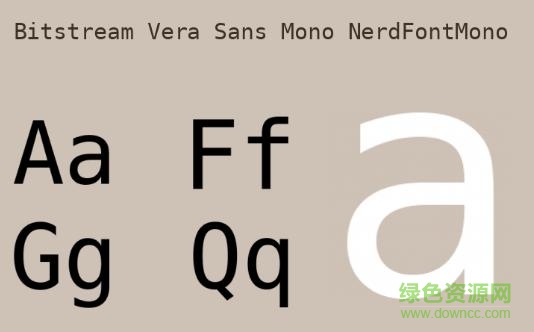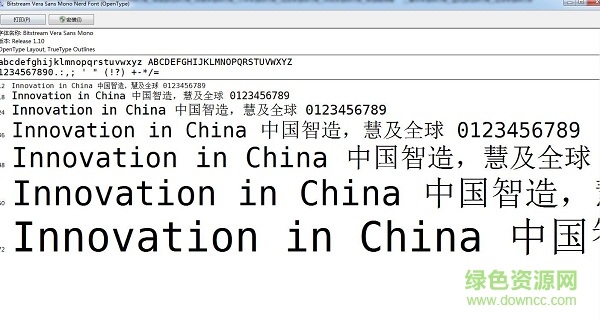
bitstream vera sans字體是一款線條清楚明朗的英文等寬字體,結(jié)構(gòu)端正,粗細(xì)一致,視覺效果不錯(cuò),適合用在電子排版以及網(wǎng)頁(yè)設(shè)計(jì)等方面,喜歡該字體的朋友快來免費(fèi)下載吧!
襯線字體的歷史比較悠久,是古羅馬時(shí)期的碑刻用字,適合用于表達(dá)傳統(tǒng),典雅,高貴,距離感。
無襯線字體相對(duì)襯線體更加親和,現(xiàn)代。從類別上大致可以分成四類:Grotesque, Neo-grotesque,Humanist和Geometric。